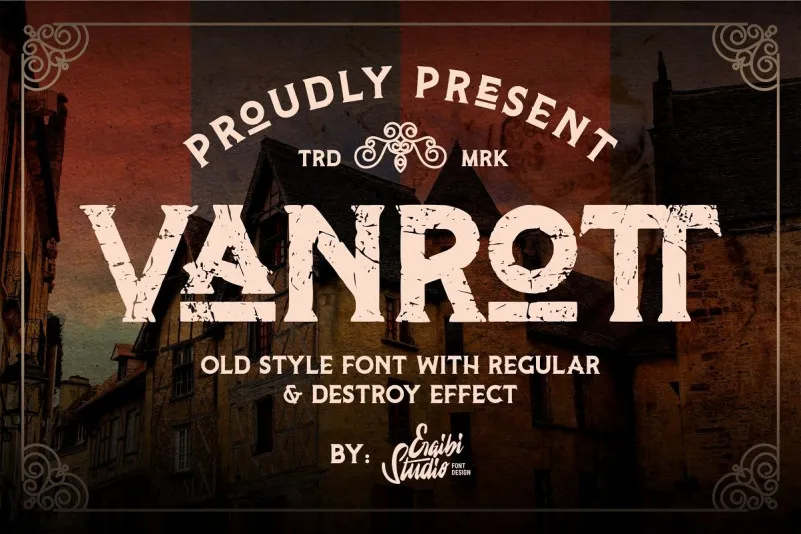
Vanrott Display Font – Download Grátis
Esta é uma inspiradora fonte para display, inspirada por fones de escrita clássica dos rótulos e logomarcas de denim. Vanrott Display Font traz um moderno e ousado estilo com efeito duplo exposição que se adequará perfeitamente a qualquer projeto design. Introduzimos o Vanrott Destroy Font, uma fonte antiga com duas escolhas regulares, transformada em uma aparência brusca e antiquada mas moderna. Ideia para aqueles que precisam de fontes para títulos, logomarcas, roupas, convites, marcações, embalagens, anúncios, entre outros. Esta tipografia é presente em letras maiúsculas, minúsculas, pontuação, símbolos, números, conjunto alternativo de estilos, ligaduras e muito mais. Sua funcionalidade é compatível com múltiplas línguas. Vanrott Display Font está disponível para a designer 0001themes, do ErgibiStudio. Este é um recurso gráfico encantador e versátil, perfeito para aqueles que estão buscando uma fonte de alta qualidade para seus projetos digitais.